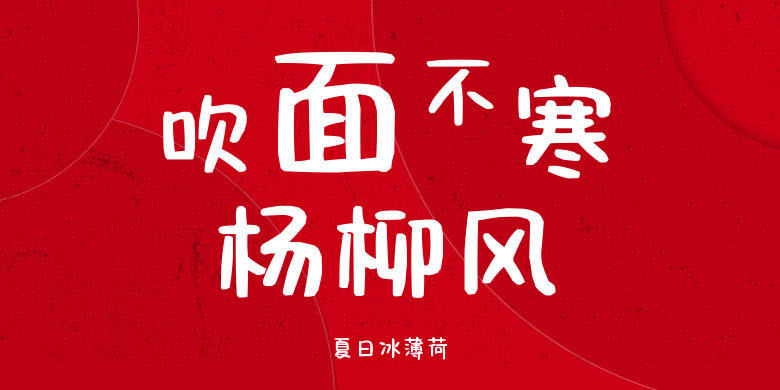
夏日冰薄荷
夏日冰薄荷,这款字体结构工整、笔画清晰,兼顾美观与易读性,适用于标题、正文、海报、包装、LOGO 等多种场景。字形优雅稳定,风格百搭耐看,适配日常排版与创意设计,让文字呈现更舒适、更具质感。夏日冰薄荷一笔一画,皆是细节,以均衡的比例、流畅的线条打造舒适视觉体验,字形端正大气,风格简约现代。无论是商业设计、品牌宣传还是日常排版,都能轻松驾驭,让文字更有格调与力量。夏日冰薄荷字体下载。